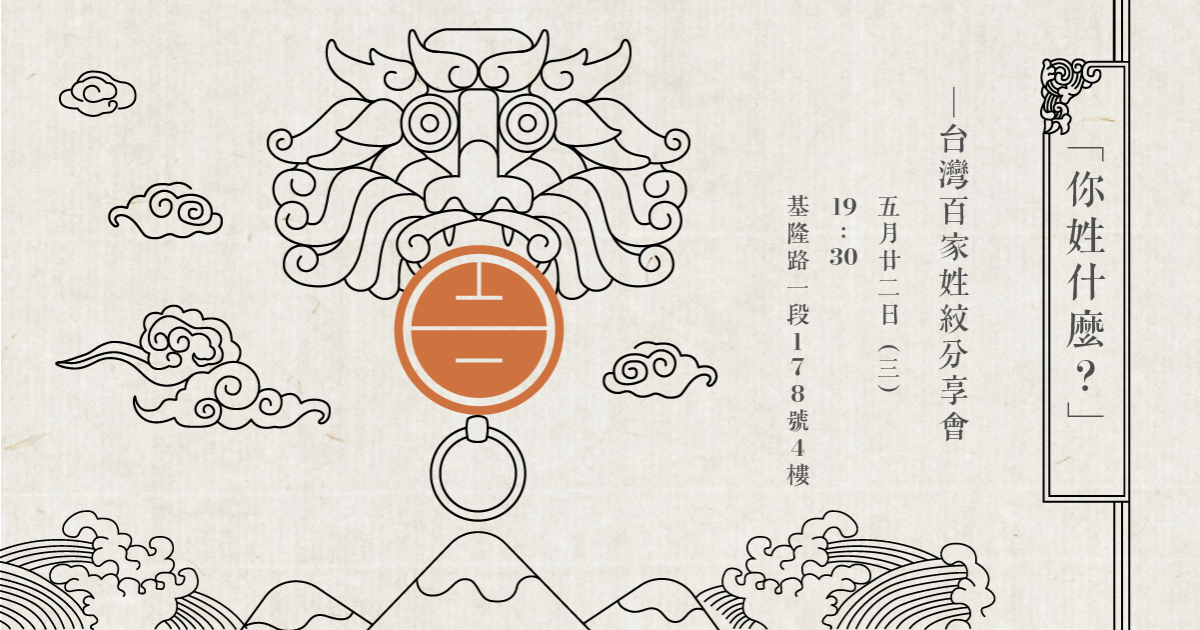
姓氏可以唸、可以寫,那也可以做成圖紋嗎?
設計一個姓只要把偏旁像拼圖拼起來就好嗎?
帶著你從漢字的圖樣藝術一路談到設計細節,
了解台灣百家姓紋的一切⋯和過程的甘苦談。
曾元濃
主修政治,但更常以怪奇的創作被看見。台灣百家姓紋不只是又一個突發奇想的產物,也是以二十出頭的視角,與幾百年傳承的文化重新互動的過程。同時為 justfont 社群小編,2017 年加入 justfont,經營各種社群頻道。